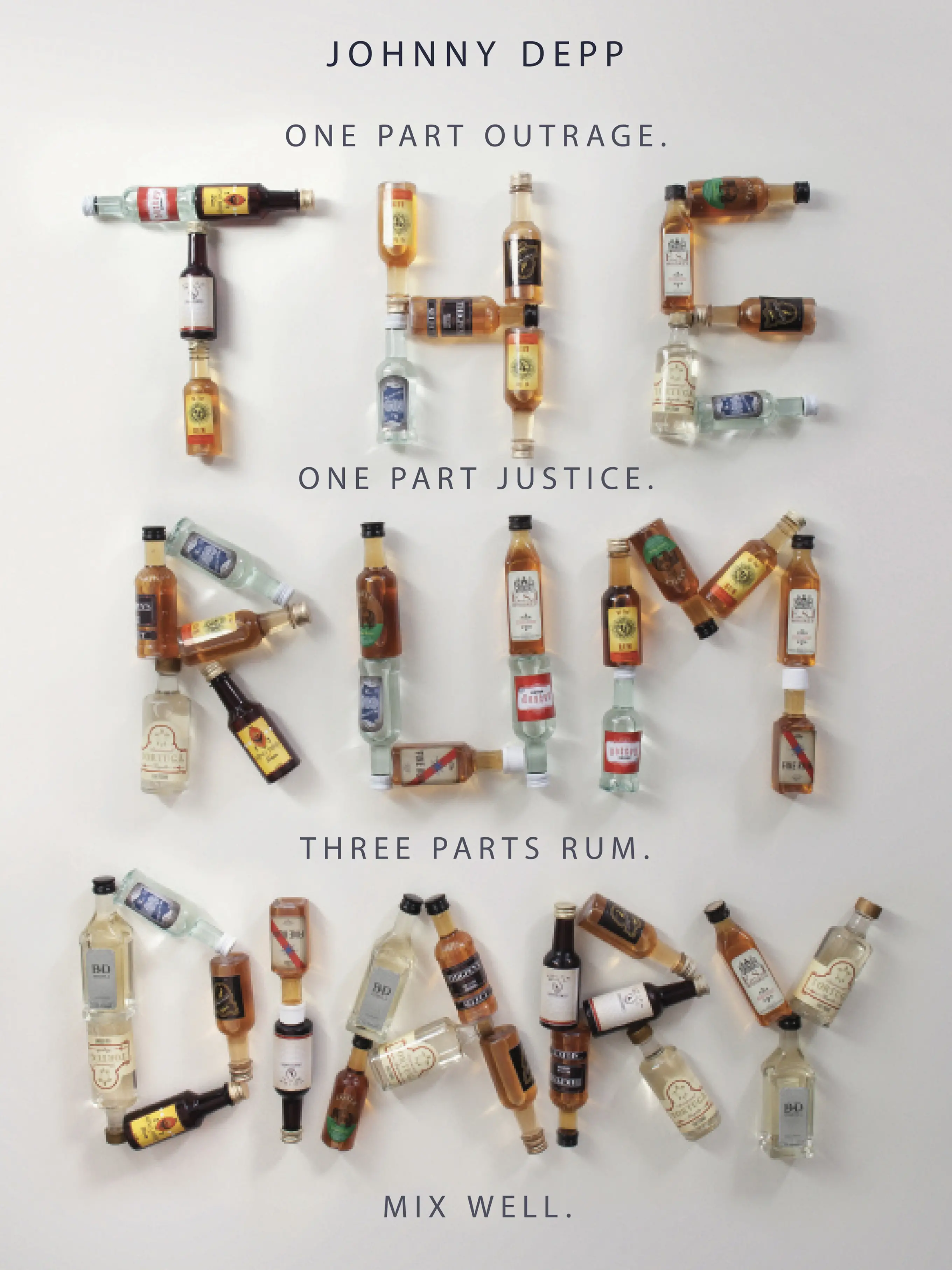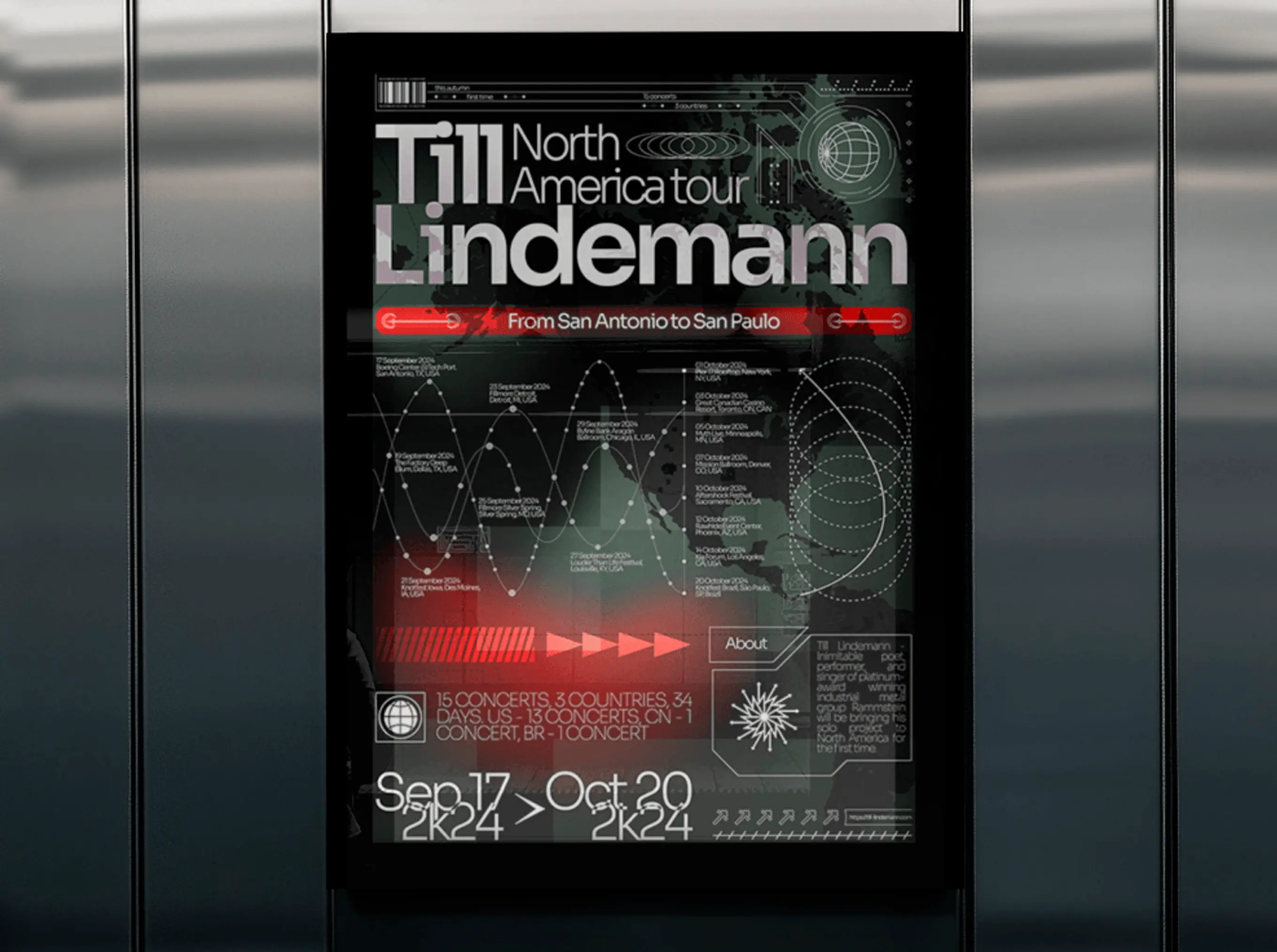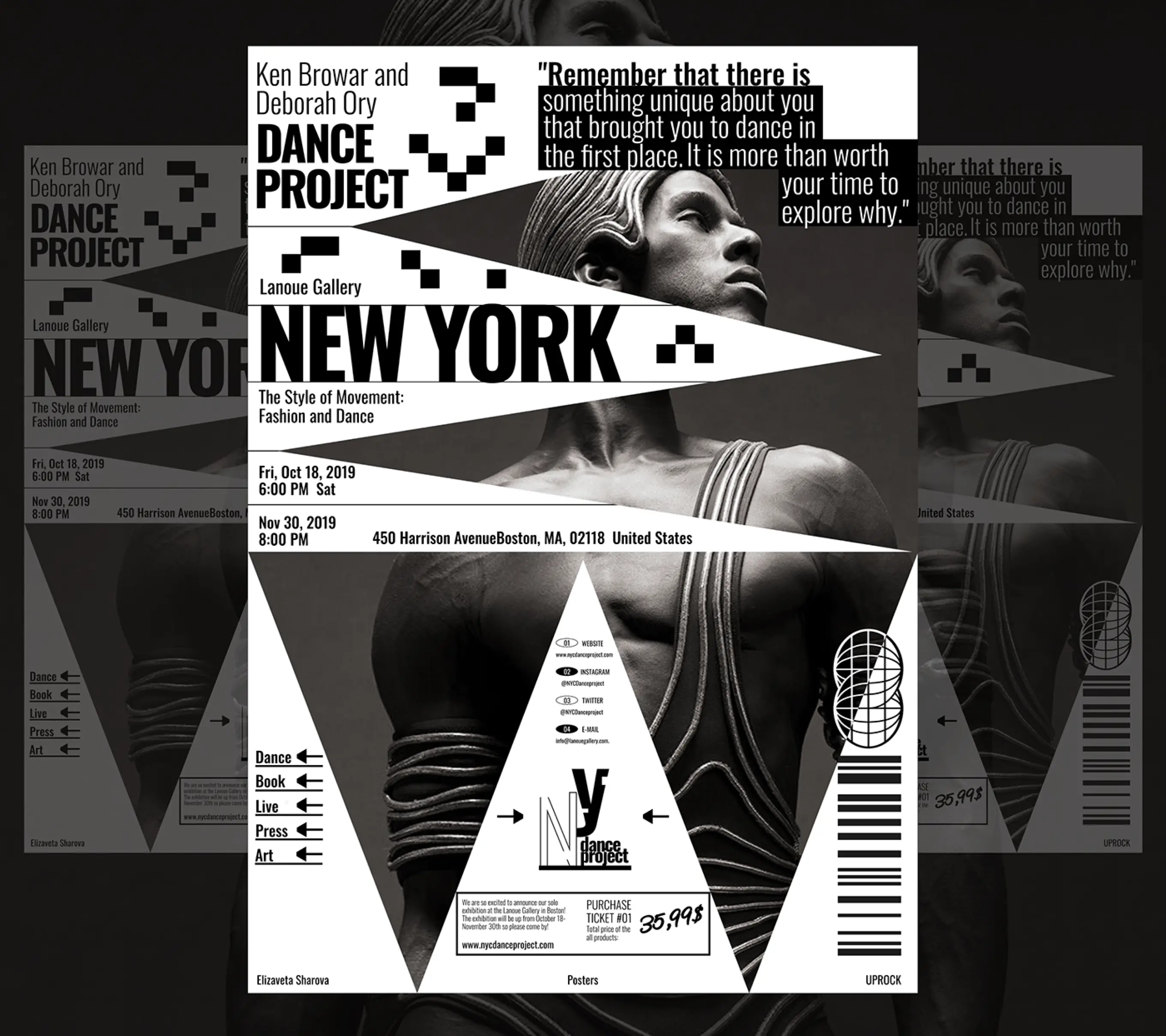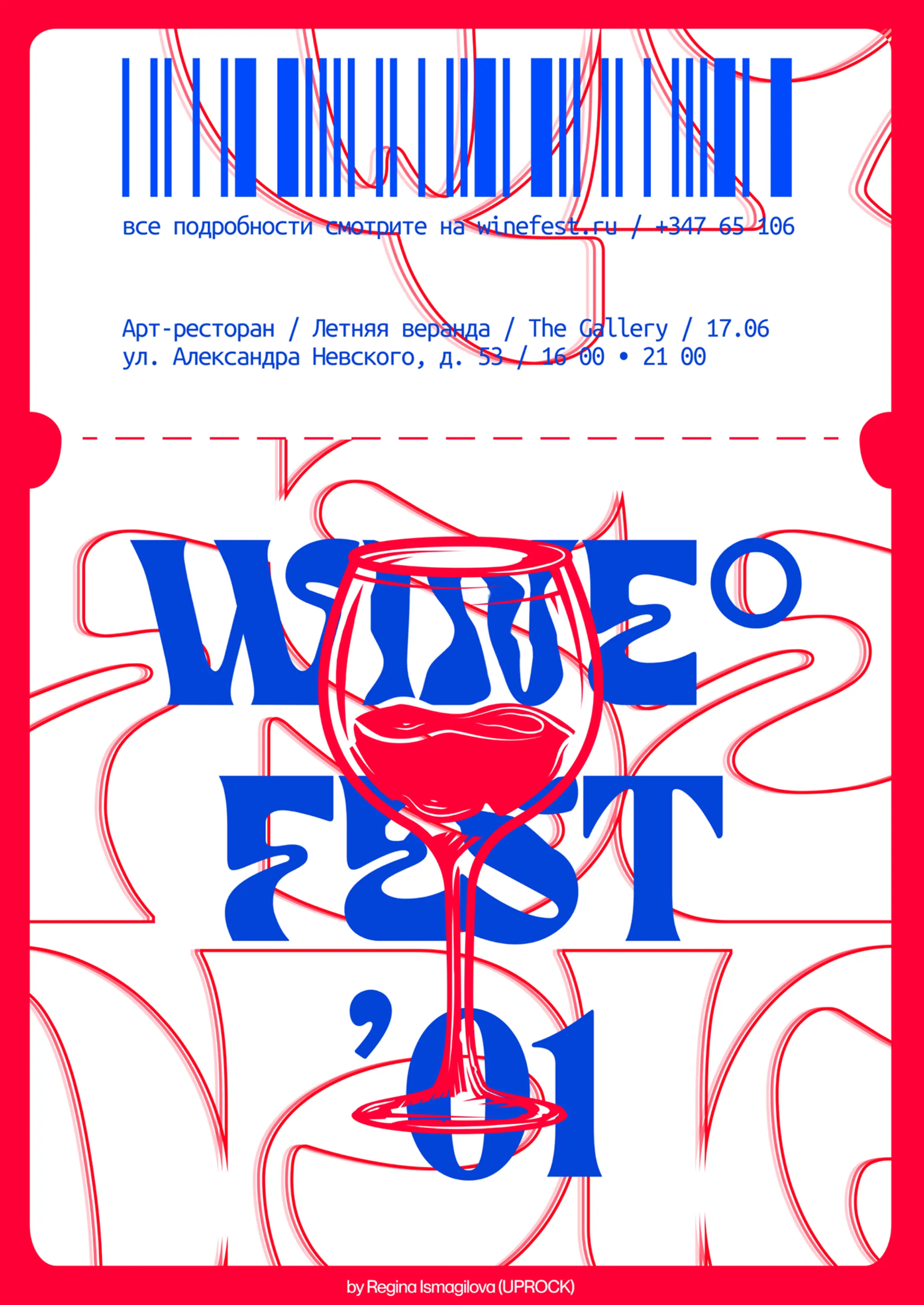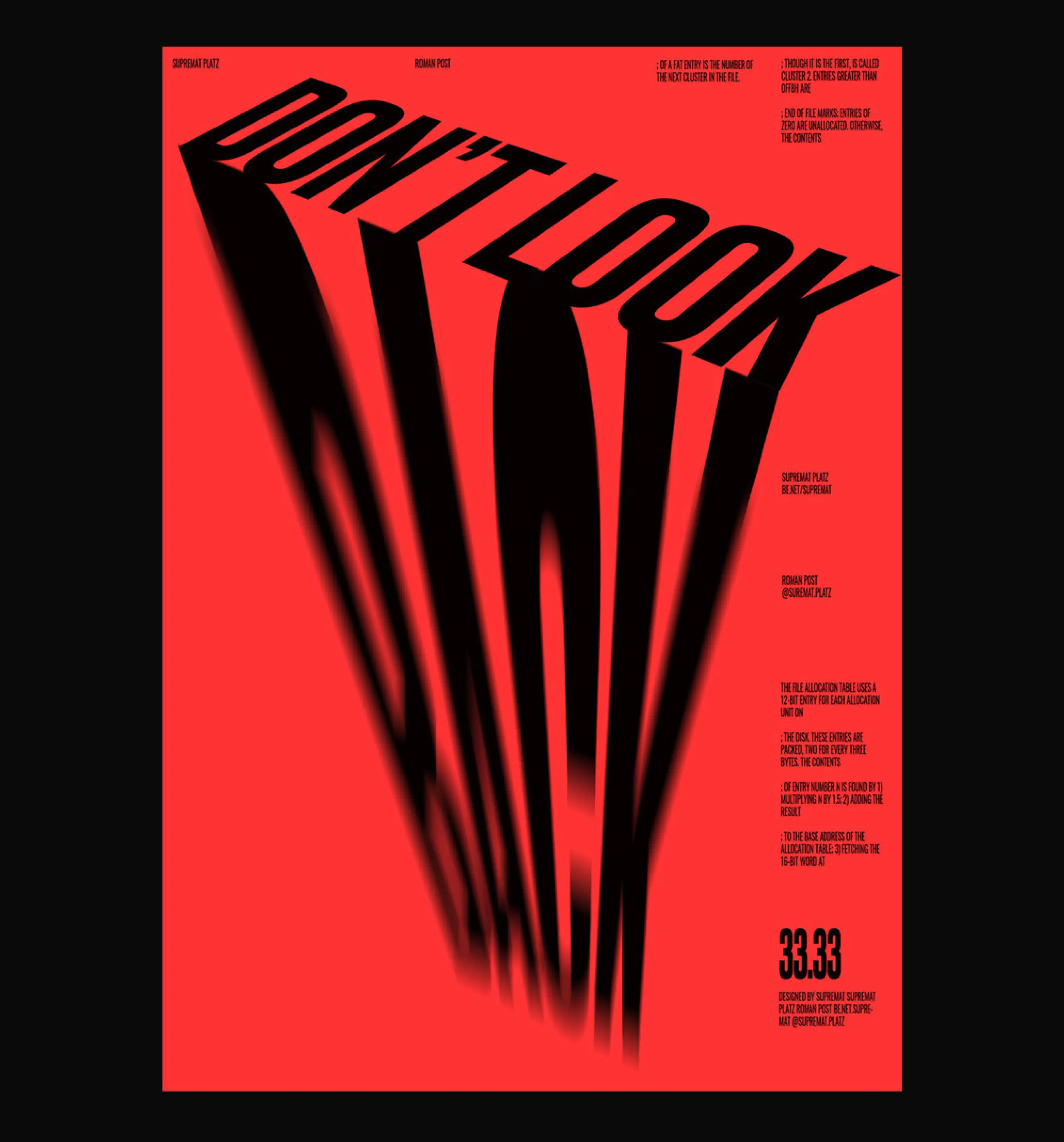
Шрифт как часть композиции
Введение
Типографика играет важнейшую роль в чтении. Однако за долгое время этот вид искусства эволюционировал и вышел за рамки просто донесения информации через текст. Типографика адаптируется к цифровому миру. Далее мы рассмотрим базовые принципы типографики, ее особенности в веб-дизайне и плакатах, а также разберем примеры, когда шрифт становится частью композиции.
Базовые принципы типографики
Если мы обратимся к основам типографики, которые закладывались со времен позднего средневековья, то увидим, что за многие века они не так уж и изменились.
Библия Иоганна Гутенберга. Середина XV в.
Библия. Современное издание
Основные принципы, которые необходимо соблюдать для достижения хорошей типографической композиции:
1. Типографическая иерархия
Типографическая иерархия информации показывает читателю, на чем следует сосредоточиться — какая информация наиболее важна, а какая просто поддерживает основные положения.
2. Выключка по левой стороне
Так как в большинстве языков чтение осуществляется слева направо, то глаз всегда возвращается к левому краю, поэтому, для удобства читателя, нужно располагать его на одном уровне.
3. Текст всегда набирается одним шрифтом
Текст всегда набирается одним шрифтом (одинакового начертания и размера). Если используются два шрифта, то необходимо избегать слишком похожих начертаний.
4. Соблюдайте пробелы
Соблюдайте пробелы в верстке, определенные золотым правилом. Поля необходимы для эстетического баланса между черным цветом текста и белым цветом бумаги. Дайте странице «дышать» и никогда не располагайте текст слишком близко к ее краю.
5. Пробелы и межбуквенный интервал
Следует обращать внимание на пробелы и межбуквенный интервал. В противном случае это приведет к неприглядным эффектам, например, коридорам или рекам.
Типографика в плакатах и веб-дизайне
Однако современные веб-сайты и приложения не выглядят как книги. Они больше похожи на плакаты. Плакаты всегда использовали более выразительные визуальные образы, чем книги. На многих из них текст выполняет не только смысловую функцию, но и визуальную — он является частью композиции.
Плакат Александра Родченко, 1924 г.
Отдельного упоминания заслуживает леттеринг, или искусство написания букв. В данном стиле сами слова и буквы выступают в качестве иллюстрации. Каждая из таких надписей уникальна, часто символы рисуются вручную, что сближает эту технику с каллиграфией.
Постер фильма «Ромовый дневник»
Соответственно, в плакатах и веб-дизайне иерархия выстраивается по отличным от книжного текста принципам:
1. Размер
Это первое, к чему обращаются дизайнеры, когда пытаются создать типографскую иерархию. И не зря. Он быстро и легко распознается читателями. Больше — важнее, меньше — менее важно.
Алекс Руденко. Студент школы UPROCK
2. Толщина
Сделать шрифт жирнее или тоньше — еще один понятный способ создания иерархии, который легко распознается даже недизайнерами.
Полина Вишнякова. Студентка школы UPROCK
3. Цвет
Цвет часто игнорируют как способ создания иерархии, но это отличный вариант. Даже использование более светлых и более темных оттенков одного цвета может создать четкую иерархию. Создание большего контраста между шрифтом и его фоном также может добавить типографской иерархии.
Ольга Ивочкина. Студентка школы UPROCK
4. Контраст размеров, толщин и стилей
Помимо контраста цветов, контраст между различными размерами, толщиной и стилями шрифта также является ключевым фактором для создания типографской иерархии.
Елизавета Шахова. Студентка школы UPROCK
5. Использование заглавных букв
Использование заглавных букв для наиболее важной информации поможет быстро отличать ее от остального текста.
Сергей Елпин. Студент школы UPROCK
6. Расположение и выравнивание
Позиционирование заголовков и подзаголовков, а также другого текста, которые дизайнер хочет выделить, может сильно повлиять на то, как текст располагается в иерархии. Например, выравнивание по центру, как правило, заставляет информацию выделяться. Размещение текста за пределами обычных полей страницы также может сделать его более заметным в иерархии страницы.
Регина Исмагилова. Студентка школы UPROCK
Шрифт и композиция
Шрифтовая композиция — это гармонично связанные между собой набор букв, блоков текста и прочих элементов текстового пространства, из которых составляется композиция.
Екатерина Иванова. Студентка школы UPROCK
Принципами построения изобразительно-шрифтовой композиции являются:
• Единство шрифта и изображения — буквы в своем написании несут единое с изображением выразительно-стилевое начало.
• Читаемость — плохо читаемые шрифты можно использовать лишь для создания спецэффектов.
• Уместность.
• Гармоничность — непродуманное смешение шрифтов приводит к дисгармонии и ощущению хаоса.
• Акцент может быть достигнут за счет контраста.
• Главный композиционный элемент — сам шрифт и его написание.
Константин Koлокольников. Студент школы UPROCK
Фигурная типографика
Слова выстроены в форме фигур, которые они отражают, тем самым усиливая сообщение.
Виктор Арес. Плакат Photoshop
Леттеринг
Анна Рольская. Меловой леттеринг в интерьере
Управляемый хаос
Смешение стилей, шрифтов и форм.
Мария Николаева. Студентка школы UPROCK
Заключение
Взяв на вооружение актуальные тенденции типографики, вы не только сможете сделать контент более интересным и приятным для чтения, но и усилите эффект вашего сообщения для аудитории.